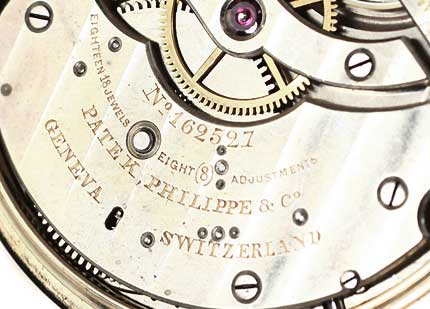
Historische Schrift, was kommt dem am nächsten?
Ich möchte von dieser Art Schrift einen kompletten Satz Schlagbuchstaben und -zahlen herstellen lassen.
Welcher Font kommt dieser Schrift und den Ziffern am nächsten?
Das ›GENEVA ...‹ ist irgendeine Klassizistische Antiqua. Könnte etwas wie Modern, Scotch Modern oder so sein.
danke für Deine Antwort! Das sieht schon mal gut aus.
Mal sehen, vielleicht hat noch jemand einen Tipp, auch zur Frage, was den Ziffern nahe kommt.
Die Ziffern sind IMHO irgendwas zwischen Walbaum und Firmin Didot. Und dann wurden die Buchstaben natürlich an die Anforderungen der Prägung angepasst.
Da sieht aber eher wie eine Gravur aus, nicht wie ein Prägung. So scheußlich wie das Ergebnis ist, wohl auch noch freihand und ohne Übung.
Gravur ja, aber ich glaube nicht, dass man bei Patek Philippe Anfänger an solche Uhren lässt. Ein besseres Foto wäre hilfreich.
Ich hoffe es jedenfalls nicht. Das Ergebnis (allein SW… bei SWITZERLAND" ist aber eher unprofessionell
Ja, Gravur, nicht Prägung. Aber trotzdem hat auch bei der scheußlichsten Gestaltung immer irgend etwas die Vorlage geliefert. In dem Fall waren IMHO die klassizistischen Antiqua Walbaum und Firmin Didot bemitleidenswerte Opfer eines beherzten gestalterischen Griff in die Kloschüssel.
Nachdem du eine Prägung von einer Gravur kaum unterscheiden kannst, hoffe ich, dass dir zumindest der Aufwand einer Handgravur bewusst ist. Wenn der Graveur einen Schriftentwurf perfekt nachvollziehen sollte, würde das die Uhr extrem verteuern.
Das ganze hat weniger mit der Entwurfsqualität zu tun, als mit der Unmöglichkeit diesen Entwurf auch halbwegs ökonomisch umzusetzen. Darüber sollte man sich im Klaren sein, bevor man ein derart präpotentes Urteil abgibt.
Das kann man in diesem Beispiel sogar sehr deutlich! Allein schon der Unterschied bei gleichen Buchstaben …
Mir ist der Unterschied sehr wohl bewusst. In meinem Beitrag habe ich nur Uwe Borchert angesprochen.
Doch, kann ich. Aber in einem Forum die Worte auf die Goldwaage zu legen ist etwas überheblich.
Zur ökonomischen Umsetzung gibt es seit vielen Jahren geeignete Schriftmuster. Wer sich anmaßt eine Antiqua zu verwenden, der soll es auch richtig machen. Ich habe gelernt für so was die passenden Schriften, welche auch in technischen Zeichnungen getuscht wurden, zu verwenden. Damit kann man drei Fliegen mit einer Klappe schlagen: Die Arbeit wird leichter, die Schriften besser lesbar und man wird nicht für einen dieser möchtegernkreativen Wünstler gehalten. Gerade Letzteres wäre für mich als bekennenden Technokraten eine schwere Beleidigung. Kreativität effizient einzusetzen bedeutet bei solchen Anwendungen in erster Linie ein handgravurtaugliches Schriftmuster auszusuchen.
Wenn du meine Kritik an deinem Beitrag als überheblich bewertest, so war das sicher von mir nicht so gemeint.
Angemerkt sei aber trotzdem, dass eine Prägung einen wesentlichen Unterschied zu einer Gravur darstellt.
Bei der Prägung kann der Entwurf weitgehend identisch umgesetzt werden. Eine gesetzte Schrift kann in ihrem Charakter wiedergegeben werden.
Im gezeigten Fall handelt es sich aber wahrscheinlich um eine Handgravur. Eine ältere Arbeit, bei der ähnlich wie beim Stahl- oder Kupferstich (Kaltnadel) die Buchstaben in Metall graviert – oder in der Technik der Radierung (chemisch) in Metall geätzt wurden. Bei dieser Technik kommen (kamen) eben keine gesetzten Schriften zum Einsatz, sondern eher eigene Schriften vom Graveur entworfen. Für diese Technik ist aber die gezeigte Schrift bestens geeignet. Vergleichbar ist das ganze mit alten, in Kupfer gestochenen Landkarten, die gerade durch die unregelmäßigen, individuell modifizierten Schriften ihren Reiz ausstrahlen.
Ich glaube auch nicht, dass hier eine konkrete Schrift zu identifizieren ist, aber die Vorschläge gehen in die richtige Richtung, auch wenn die Serifen für eine klassizistische Schrift zu prominent sind, aber das mag an der technischen Umsetzung liegen. URWs Torino geht so in die Richtung.
Wenn ich mir die Zahlen anschaue, denke ich daher eher an ein späte Barocktype wie Bulmer oder Bell, aber das sind nur grobe Orientierungspunkte.
PS: Ob nun Goudy Modern eine Renaissance- oder eine klassizistische Antiqua ist, kann wohl gleichermaßen bestritten werden.